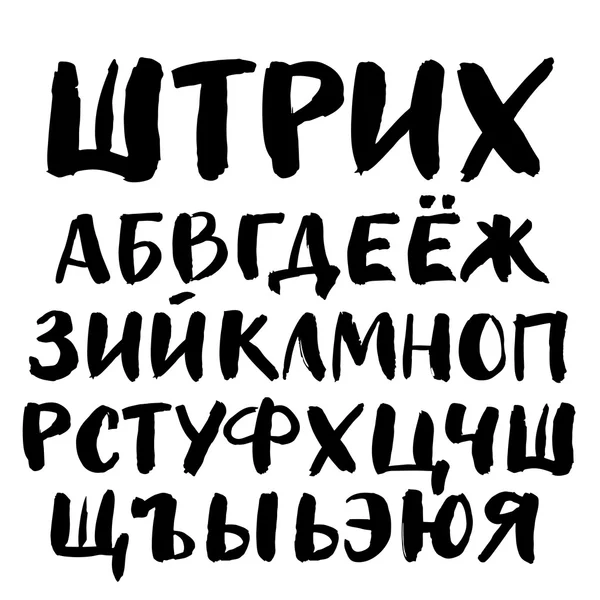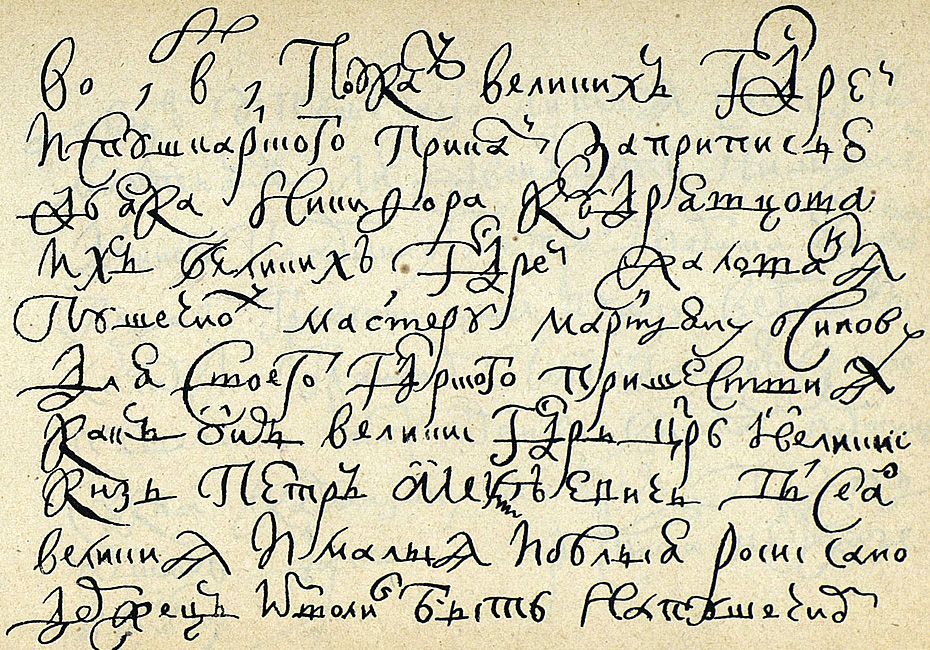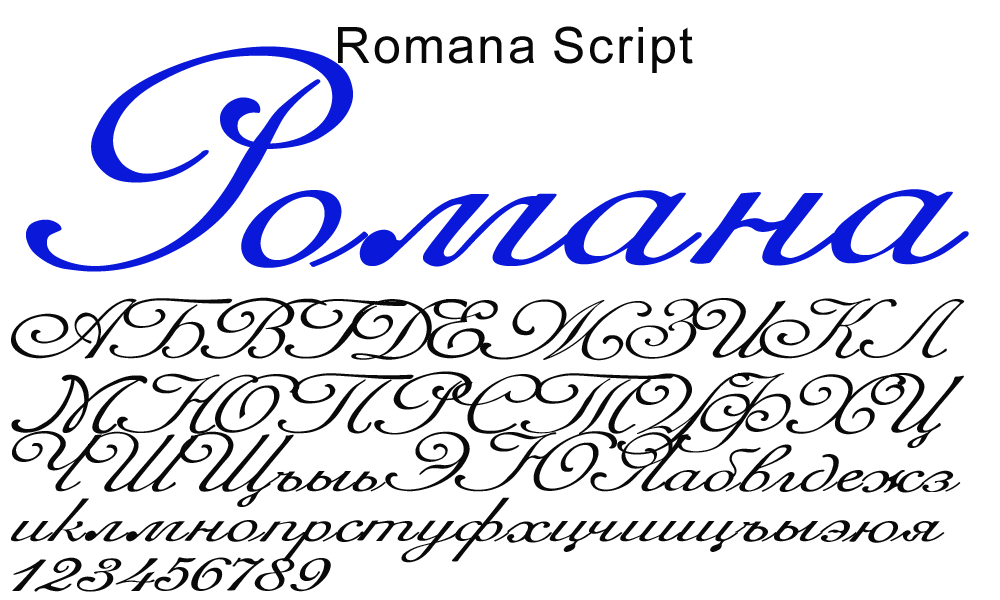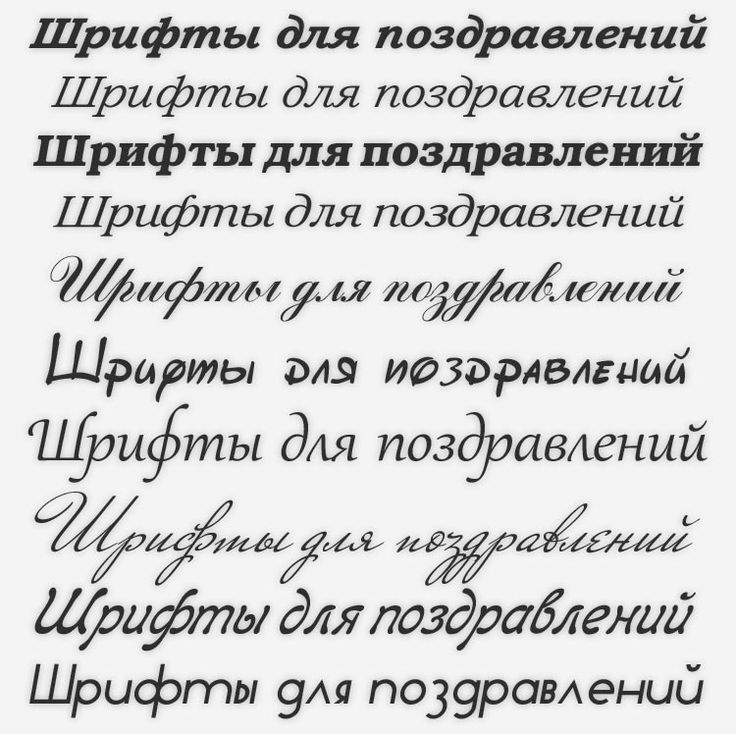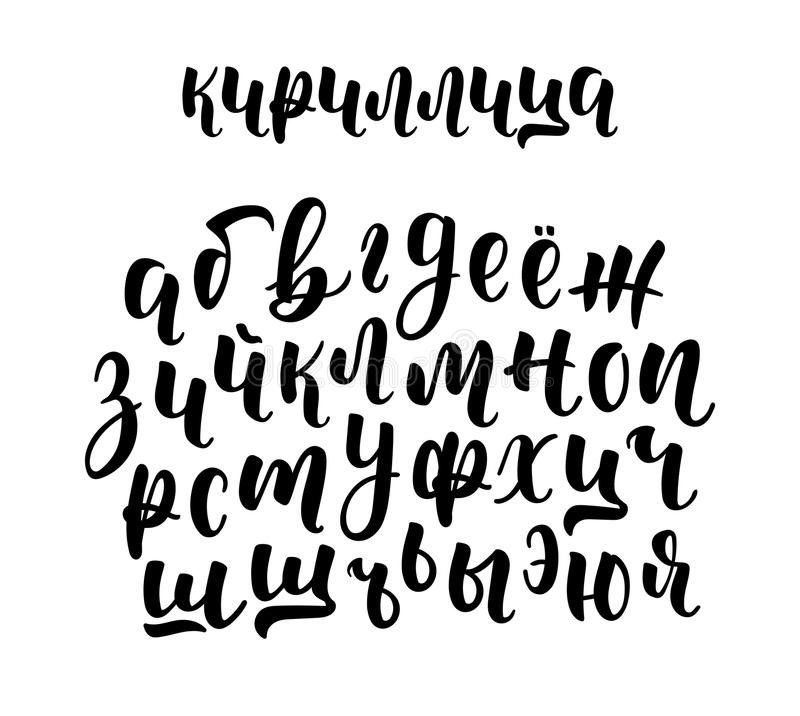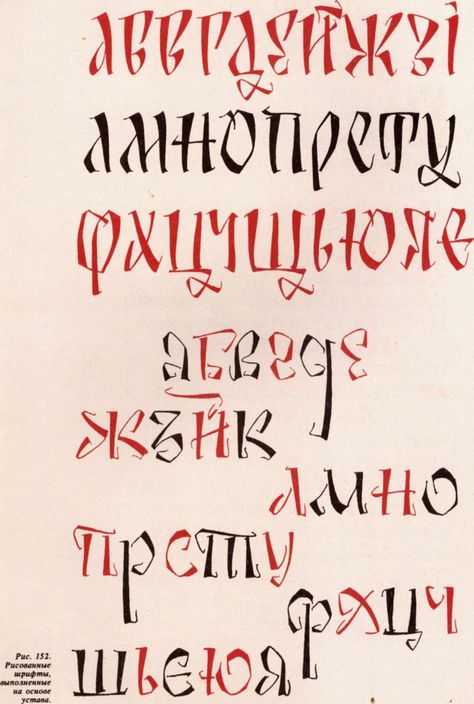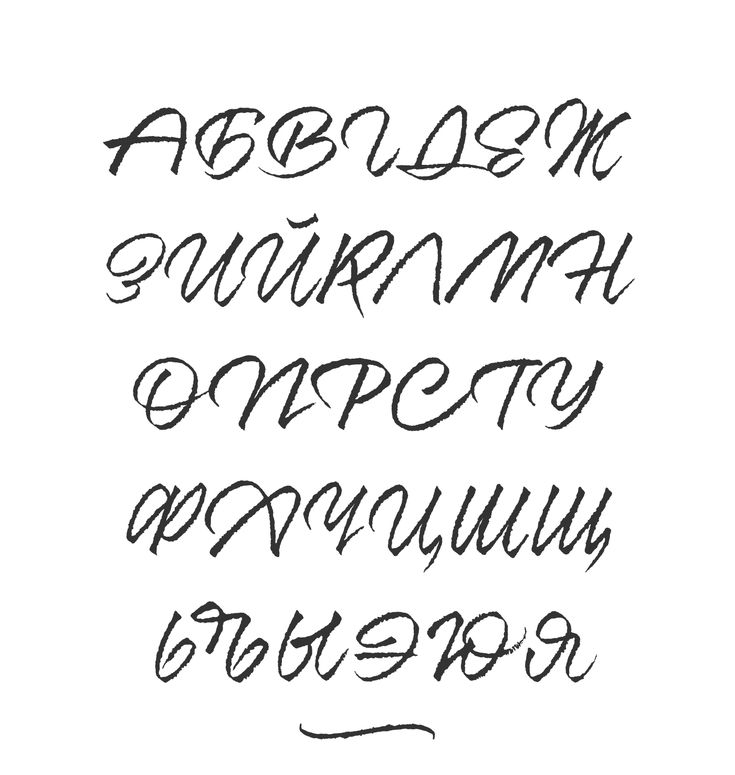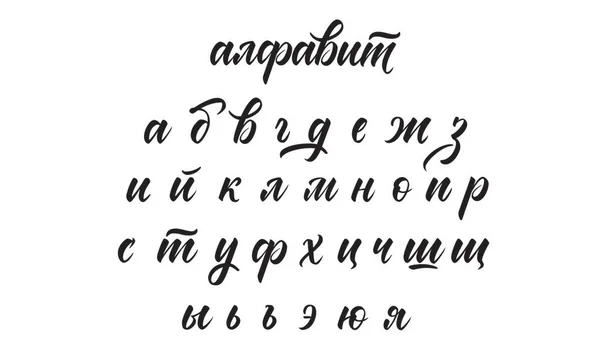
— У вас же такие славные письменные принадлежности, и сколько у вас карандашей, сколько перьев, какая плотная, славная бумага… И какой славный у вас кабинет!
Ф.М. Достоевский, «Идиот»
Сначала пользовались рукописными шрифтами. Ими пользовались умелые переписчики-каллиграфы, в силу трудоемкости изготовления рукописей превращавшие каждую в произведение искусства.
С изобретением книгопечатания искусство каллиграфии ушло в прошлое. Стало не нужным выводить каждую рукописную загогулину, требовалось располагать стандартные заранее заготовленные литеры в определенной последовательности. Этим занимались профессиональные типографы. Читатели получали готовый стандартизированный продукт, а сами продолжали писать письма или сочинять рукописи вручную, в силу того что не существовало пригодных для индивидуальной работы типографий.
Положение сдвинулось с мертвой точки с изобретением пишущих машинок.
Новый виток технического прогресса в области машинописной техники – изобретение компьютеров – возвратил индивидуальности почерка былое величие. Шрифты оставались стандартными, но теперь их выбирали по собственному вкусу и усмотрению.
Желаемая механизация с сохранением индивидуальных особенностей? Безусловно так. Но давайте сравним всем нам знакомые компьютерные шрифты с рукописными: частично с познавательной целью, частично – с целью предаться ностальгии об ушедшем в прошлое великом и незабвенном искусстве каллиграфии.
«Мама мыла раму» — это все помнят, возьмем что-нибудь столь же незамысловатое, при этом возрастное.
Это из прописей 1837 года. Пушкин обучаться по ним не успевал, но вряд ли образчики его времени представляли собой что-то принципиально иное. Школьные прописи – чуточку больше в них витиеватости или чуточку меньше – и есть школьные прописи: своей рукой вывести правильную закорючку затруднительно, но в конце концов их однообразие приедается.
Что это за наука, в самом деле, в которой главное – соблюсти правильный наклон?
Как наставлял главного героя известного романа В. Каверина «Два капитанов» нелюбимый отчим: палочки должны быть попендикулярны.
Также необходимо соблюдать однообразный отступ слов друг от друга.
Плюс гармоничная толщина линий, достигаемая наклоном пера и силой давления на бумагу.
И разумеется, общая, приятная глазу плавность начертаний.
Для соблюдения правил требовалось правильно держать в пальцах перо – главное производственное орудие каллиграфа…
…и сохранять правильную осанку.
Для обучения чистописанию – как для обучения любому другому ремеслу – необходимы были годы упорного труда: в школах, бизнес-колледжах, на курсах каллиграфии, весьма распространенных в начале прошлого века.
Но если человек овладевал этим искусством, — о! он превращался в гуру, которому доступны любые профессиональные изящества. В первую очередь почерки – говоря компьютерным языком, шрифты. Тут, благодаря индивидуальности мастера, предела совершенствованию не было. Вглядитесь в эти образчики буквенных начертаний, от относительно простых до самых замысловатых, и оцените их нестареющую красоту.
От таких почерков до живописи – один шаг. Отчего бы человеку, овладевшему столь замысловатыми начертаниями, не проявить себя в смежной области? И проявляли.
Живописали каллиграфы в близком им стиле: каллиграфического рисунка, зачастую с прикладными целями либо просто для удовольствия.
Естественно, так рисовали не учащиеся девочки, а люди в возрасте, умудренные достигнутым опытом – как и полагается мастерам своего дела.
На этом, собственно, можно было бы и закончить, но хочется привести небольшой отрывок из романа «Идиот», откуда позаимствован эпиграф к настоящему посту.
«— Ого! — вскричал генерал, смотря на образчик каллиграфии, представленный князем: — да ведь это пропись! Да и пропись-то редкая! Посмотри-ка, Ганя, каков талант!
На толстом веленевом листе князь написал средневековым русским шрифтом фразу:
“Смиренный игумен Пафнутий руку приложил”.
— Вот это, — разъяснял князь с чрезвычайным удовольствием и одушевлением, — это собственная подпись игумена Пафнутия со снимка четырнадцатого столетия. Они превосходно подписывались, все эти наши старые игумены и митрополиты, и с каким иногда вкусом, с каким старанием! Неужели у вас нет хоть Погодинского издания, генерал? Потом я вот тут написал другим шрифтом: это круглый, крупный французский шрифт, прошлого столетия, иные буквы даже иначе писались, шрифт площадной, шрифт публичных писцов, заимствованный с их образчиков (у меня был один), — согласитесь сами, что он не без достоинств.
Взгляните на эти круглые д, а. Я перевел французский характер в русские буквы, что очень трудно, а вышло удачно. Вот и еще прекрасный и оригинальный шрифт, вот эта фраза: “усердие всё превозмогает”. Это шрифт русский писарский или, если хотите, военно-писарский. Так пишется казенная бумага к важному лицу, тоже круглый шрифт, славный, черный шрифт, черно написано, но с замечательным вкусом. Каллиграф не допустил бы этих росчерков или, лучше сказать, этих попыток расчеркнуться, вот этих недоконченных полухвостиков, — замечаете, — а в целом, посмотрите, оно составляет ведь характер, и, право, вся тут военно-писарская душа проглянула: разгуляться бы и хотелось, и талант просится, да воротник военный туго на крючек стянут, дисциплина и в почерке вышла, прелесть! Это недавно меня один образчик такой поразил, случайно нашел, да еще где? в Швейцарии! Ну, вот, это простой, обыкновенный и чистейший английский шрифт: дальше уж изящество не может идти, тут всё прелесть, бисер, жемчуг; это закончено; но вот и вариация, и опять французская, я ее у одного французского путешествующего комми заимствовал: тот же английский шрифт, но черная; линия капельку почернее и потолще, чем в английском, ан — пропорция света и нарушена; и заметьте тоже: овал изменен, капельку круглее и вдобавок позволен росчерк, а росчерк это наиопаснейшая вещь! Росчерк требует необыкновенного вкуса; но если только он удался, если только найдена пропорция, то эдакой шрифт ни с чем не сравним, так даже, что можно влюбиться в него.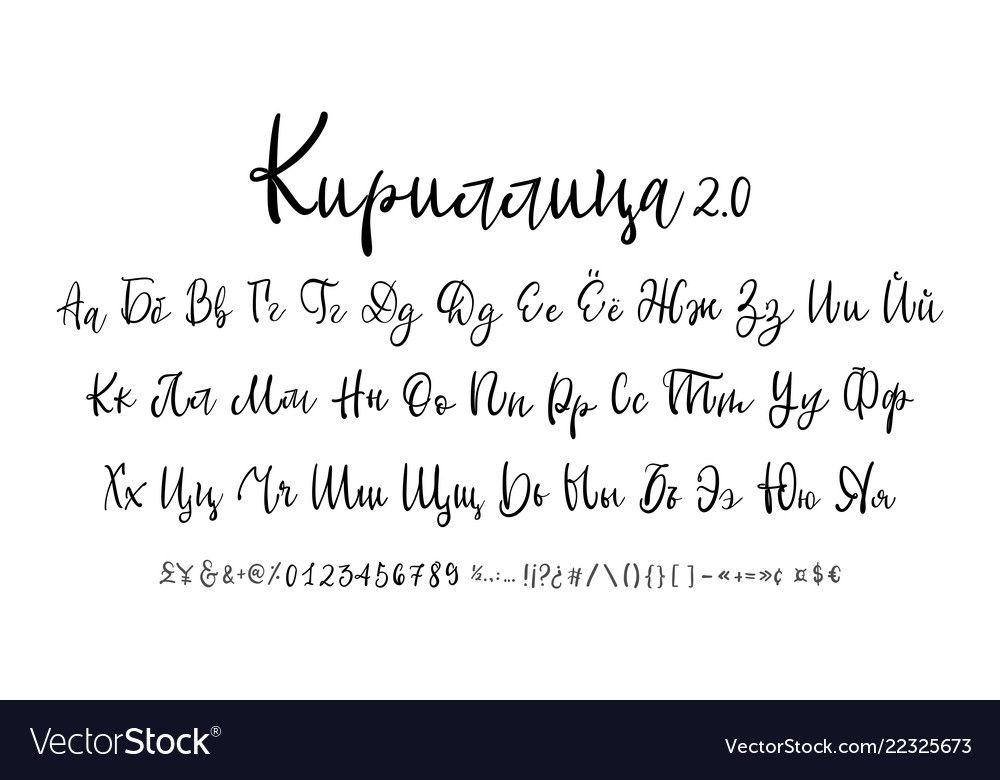